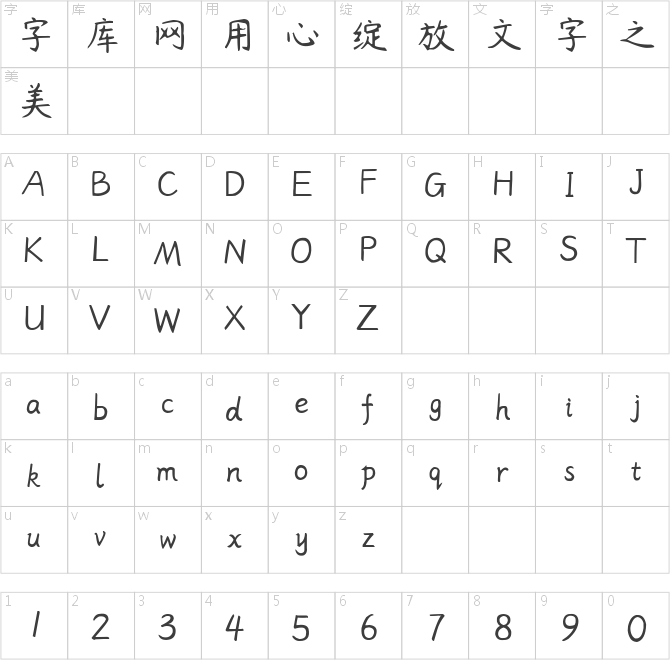
楊任東竹石體-Regular 詳情頁
字體名稱: 楊任東竹石體-
楊任東竹石體-Regular
楊任東竹石體-Regular介紹
楊任東竹石體-Regular字體字庫是一款讓人賞心悅目、百看不厭的中文字體,適合各類廣告和產品包裝設計應用,字體大小4.1MB,格式為ttf字體,上傳用戶是九醬,作者/版權方為楊任東